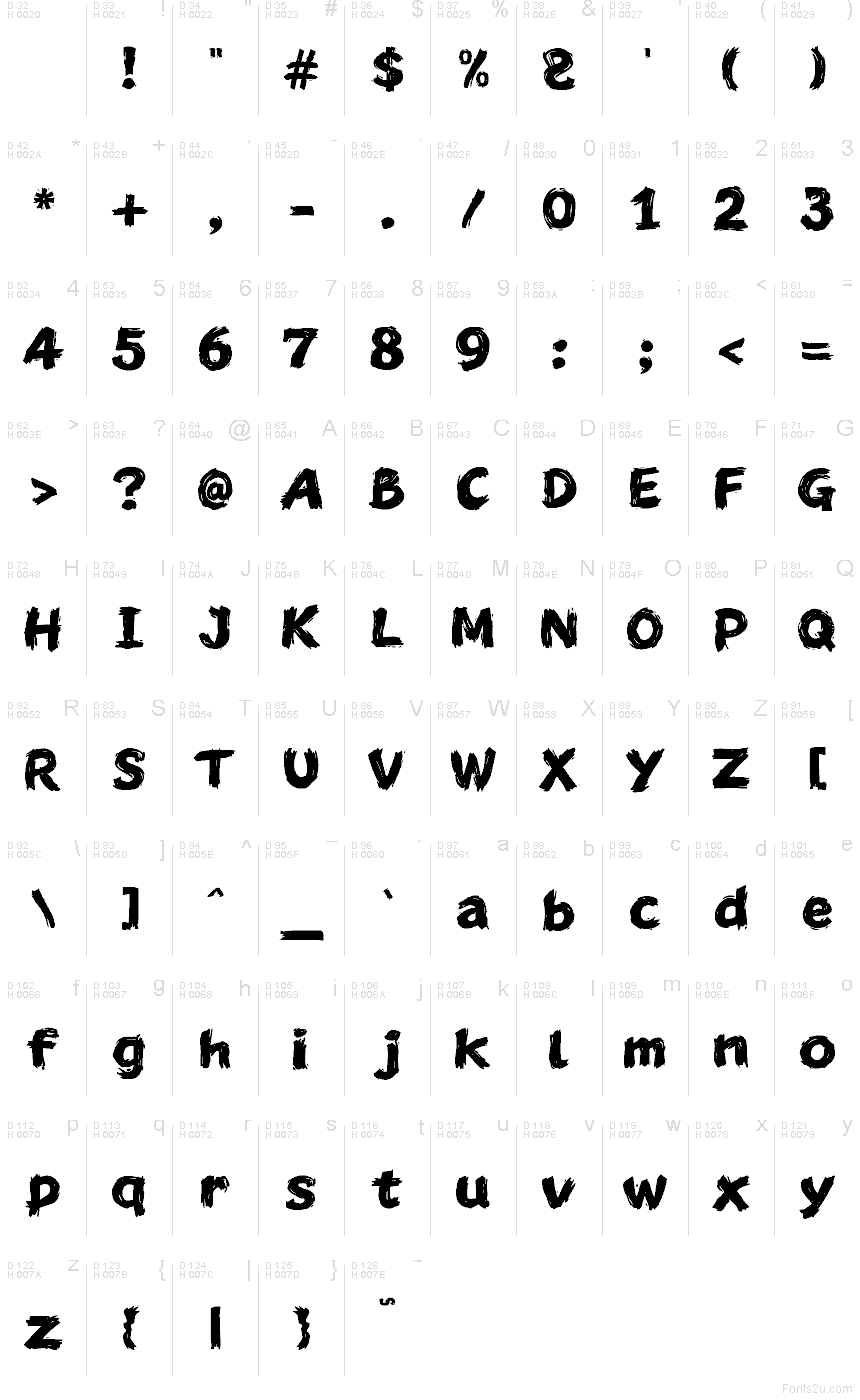
La Meute Furieuse di BlackFridayFont è un font gratuito in stile dry-brush con un carattere ruvido e dipinto a mano. Le lettere sembrano tracciate velocemente, con tratti spessi, bordi sfrangiati e una pressione irregolare che conferisce un ritmo vivace e dinamico.
Si adatta perfettamente a titoli di poster, grafiche musicali, design streetwear, flyer ed etichette audaci che richiedono carattere invece di una rifinitura classica. Ideale soprattutto per titoli brevi – la texture larga del pennello conferisce anche a poche parole l'aspetto di qualcosa creato in fretta.